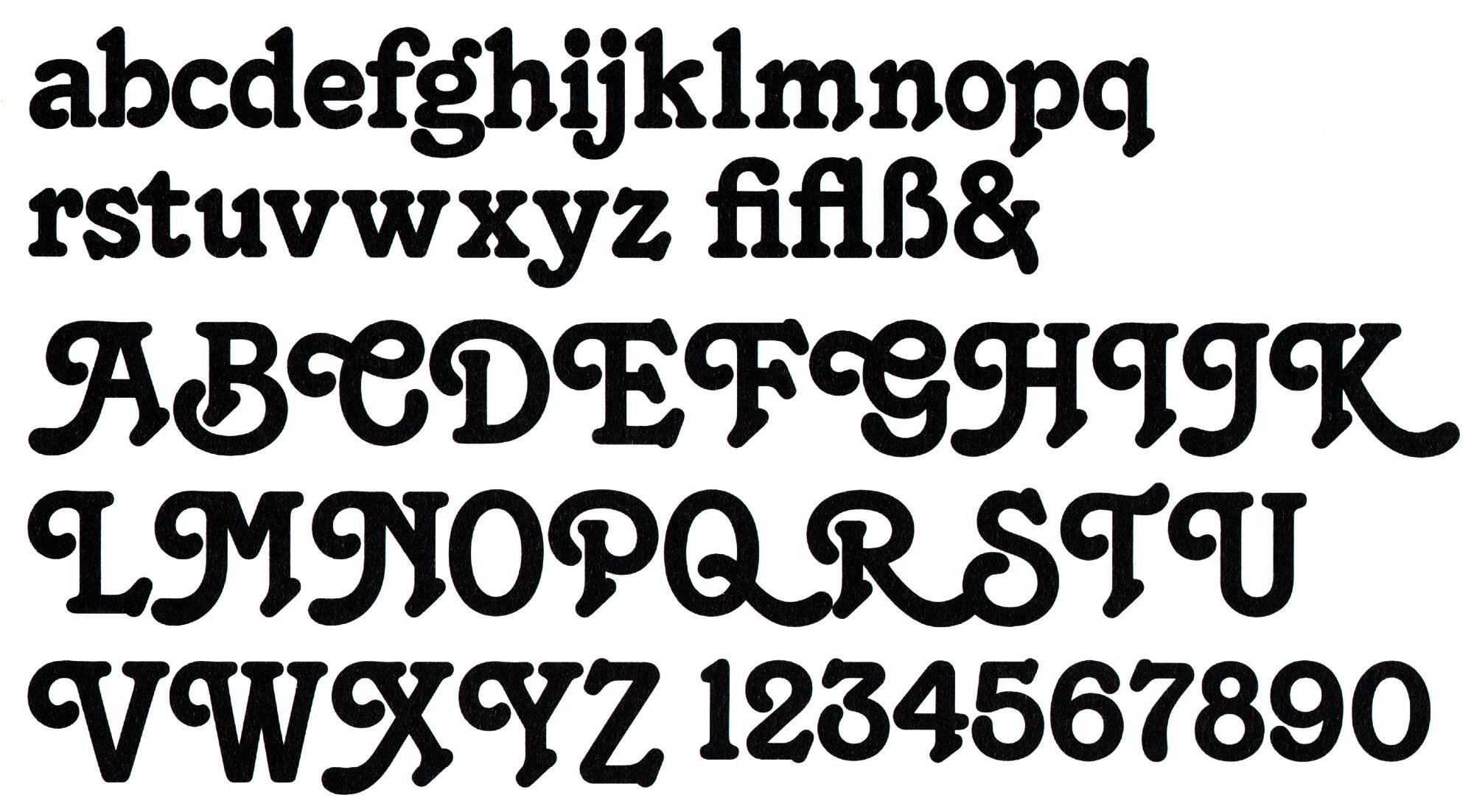
• 1974
• Serifen:
• sans
• Antiqua dekorativ
Die Tango von Colin Brignall ist eine Antiqua mit abgerundeten Strichen und Schwungbuchstaben-Versalien. Letztere stehen nicht auf der Grundlinie sondern richten sich nach den Unterlängen der Kleinbuchstaben aus. Die Schrift erschien in den 1970er-Jahren über Letraset und als Fotosatzschrift.
Digitale Versionen gibt es heute zum Beispiel von ITC, Bitstream und Tilde.